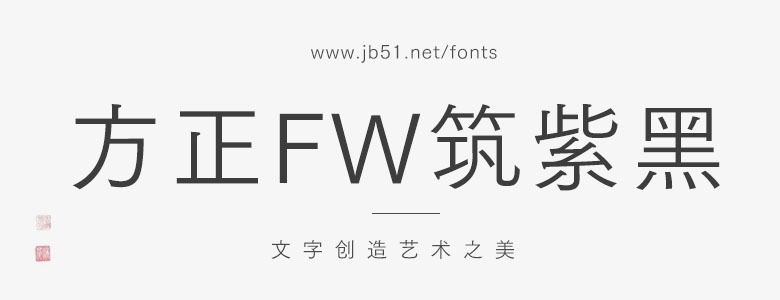
筑紫黑家族在設(shè)計(jì)上一直基于與2003年發(fā)布的筑紫宋體家族一致這一原則進(jìn)行新的開(kāi)發(fā)。使用范圍廣,包括書(shū)籍、雜志、目錄、廣告單等,重視文字的質(zhì)感,保證要求品位時(shí)也可以滿足要求。這是由八個(gè)字重組成的黑體家族系列,正文、解說(shuō)詞、小標(biāo)題、大標(biāo)題均設(shè)計(jì)為最佳表達(dá)方式。
筑紫黑體的書(shū)法風(fēng)格將現(xiàn)代的鮮明感、潔凈的堅(jiān)硬感、經(jīng)典的趣味以及柔和融為一體,既正統(tǒng)又給人新鮮感。在重視現(xiàn)代字體設(shè)計(jì)的主流“均質(zhì)性和均勻性”的同時(shí),又不忘記“文字是邊用手寫(xiě)邊設(shè)計(jì)形成的”這一點(diǎn),與筑紫宋體同樣地使“寫(xiě)”這一手的動(dòng)作坦率地表現(xiàn)在文字中。能看出“寫(xiě)”這一動(dòng)作,是基本字體的使命“鮮明地突出文章的含義”這一表現(xiàn)力的源泉。在建立、使用和閱讀字體的各個(gè)行為中重新驗(yàn)證了可以表現(xiàn)現(xiàn)代世界的黑體的使命和作用,這是設(shè)計(jì)的根本,筑紫黑體就是在對(duì)這個(gè)根本的重新審視中產(chǎn)生的。